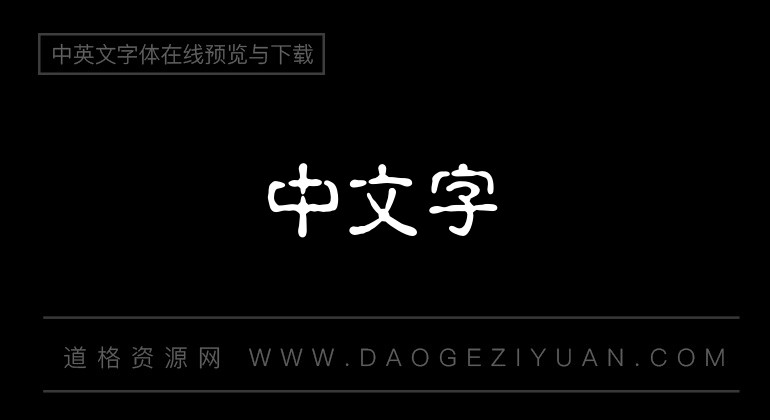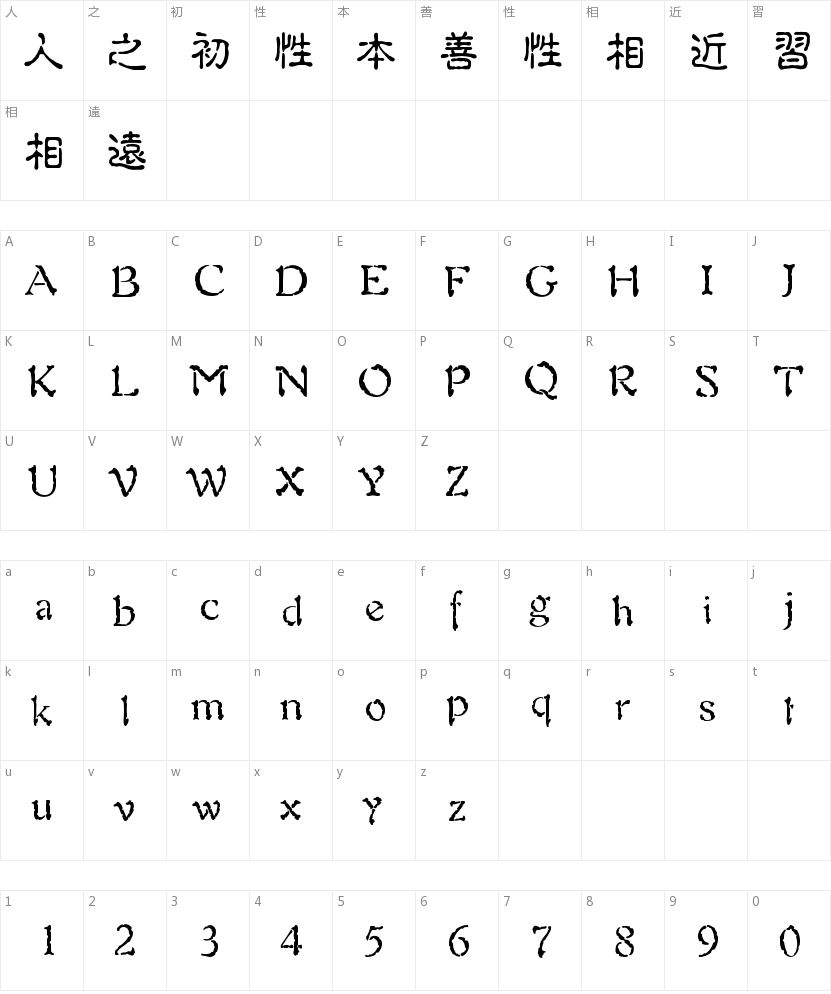
蒙纳繁古印
蒙纳繁古印字体是一款简洁的中文字体。该字体的特点是在保留原有的繁体字形的基础上,将更多的笔画精细化,从而让字体看起来更加精致。它采用精致的曲线线条,具有良好的空间感和视觉效果,可以提升文字的质感。此外,它还具有较强的识别性,可以更好地传达文字的意义。
蒙纳繁古印是一款非常不错的手写艺术字体,具有很好的视觉感,适合于文化类的宣传设计、商业类品牌的广告和产品包装设计以及个性化文字排版等较多场景。